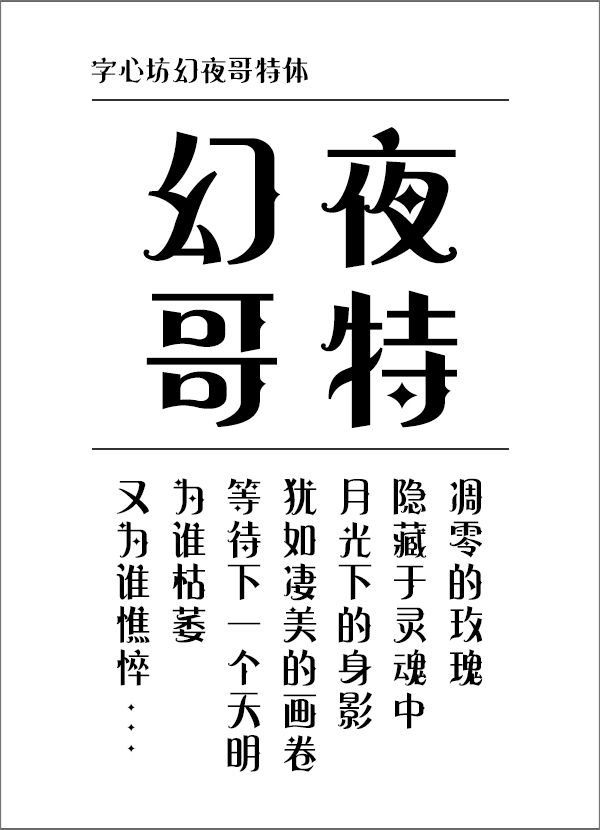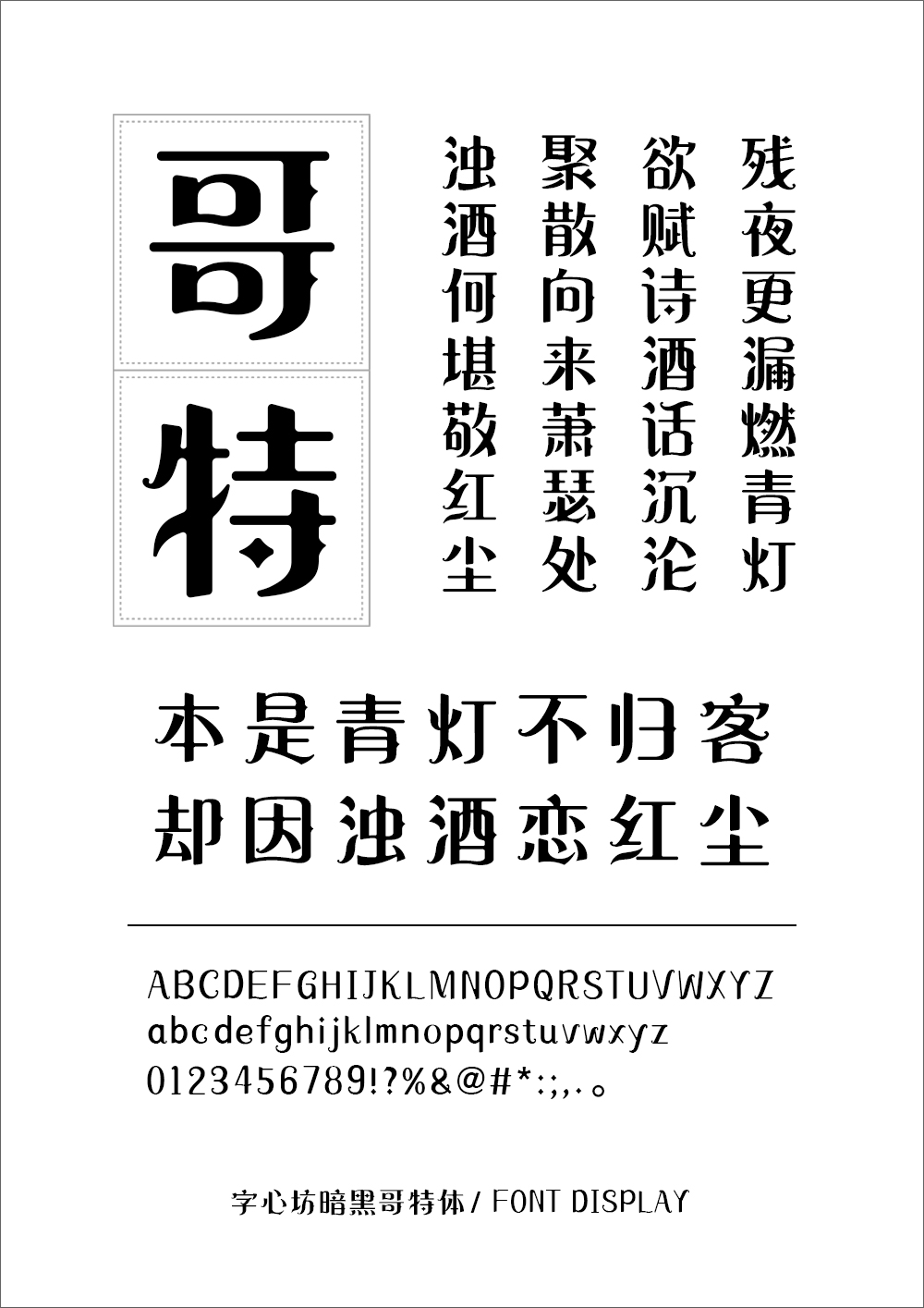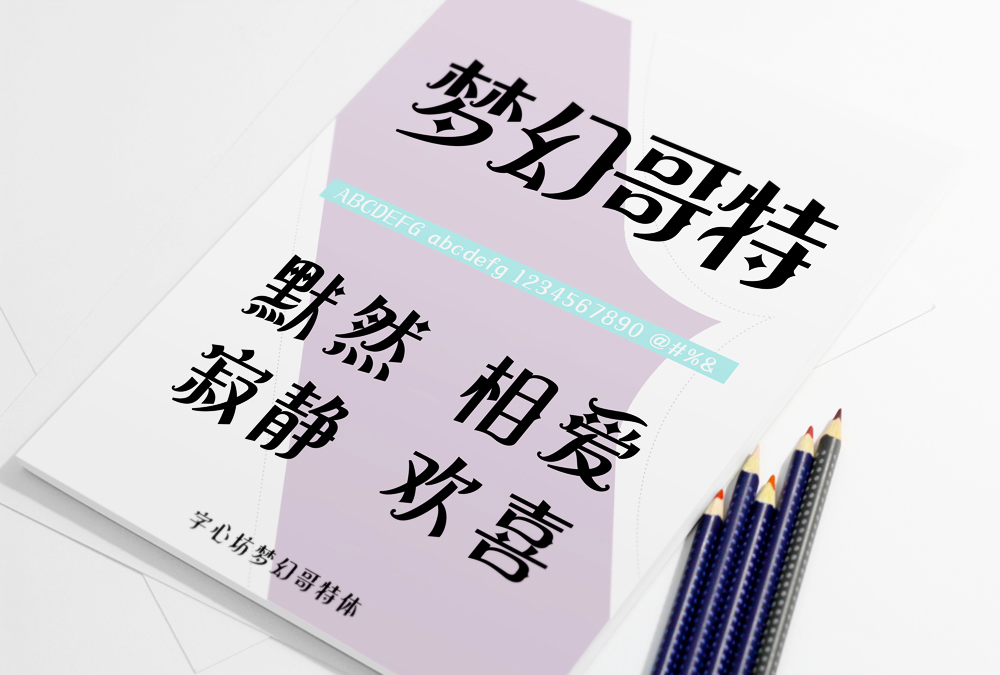
字心坊哥特体系列
该系列共分为字心坊梦幻哥特体、字心坊幻夜哥特体和字心坊暗黑哥特体3个字库。
该字体是一款哥特风字体,字体独特,新颖华丽。汉字艺术与西方文字的融合,如夜空中闪烁着暗黑光芒;个性鲜明的字体特征,散发着神秘而高冷的气息。在华丽而不失婉约中,感受哥特风的魅力。
字体风格:哥特风/ 华丽 / 时尚